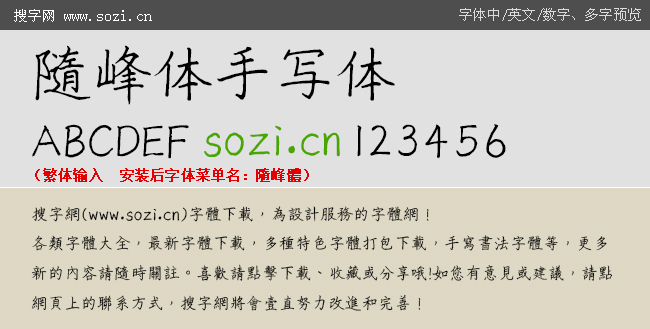
隨峰體手寫體
搜字網(wǎng)給大家提供一款隨峰體手寫體中文字體下載,隨峰體手寫體是一款手寫風(fēng)格的硬筆書法字體,字體書寫流暢,簡(jiǎn)潔大方,具有很好的視覺效果。適用于海報(bào)設(shè)計(jì)、包裝設(shè)計(jì)、廣告設(shè)計(jì)等場(chǎng)景。